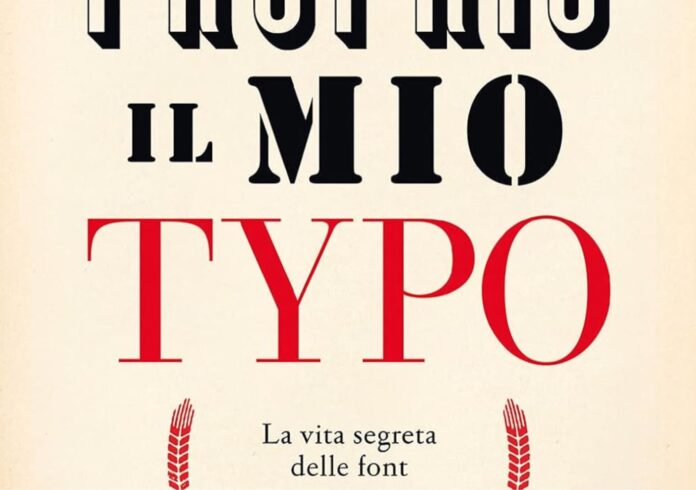
Cosa vuol dire fare un libro? Come si costruisce? Che cosa serve? Tra self publishing e stampanti laser o a getto d’inchiostro di alta qualità le possibilità di far uscire dal cassetto il nostro romanzo o il nostro poema aumenta. Ma il vero problema è un altro.
Far da sé non sempre è garanzia di qualità perché il libro, oltre a essere scritto bene e rispettando alcune convenzioni chiave, è anche un oggetto di artigianato che richiede cura e sapienza nel modo con il quale viene montato. Ecco dunque che serve sapere cose che non sono quelle semplicemente della scrittura. Almeno, non solo.
Font Ergo Sum, gratis il libro che racconta i font come non li avete mai pensati
Per molti i caratteri tipografici, font in inglese, sono una serie di voci nel menu omonimo all’interno delle app di Word, Photoshop, Illustrator e tanti altri ancora, che accompagnano i nostri documenti dando loro una “impronta” che cambia la leggibilità, ma anche l’emozione di un testo, e di conseguenza la sua forza nel lettore.
Ma i caratteri, come molte altre opere dell’ingegno umano sono il frutto di mille storie, che affondano le radici degli ultimi cinquecento anni e che sono stati capaci di rivoluzionare il mondo della comunicazione, così come lo fanno ancora oggi.
Sei proprio il mio typo. La vita segreta delle font
Piccola rivoluzione quando è uscito negli Usa, quesot saggio colto di Simon Garfield è un punto di riferimento per capire la storia di un aspetto molto particolare della tipografia. Pressoché sconosciute fino a vent’anni fa, grazie all’avvento della tecnologia informatica oggi le font sono a tutti gli effetti protagoniste del nostro quotidiano. Ma quali sono state le tappe che le hanno portate a uscire dalla ristretta cerchia di addetti ai lavori e di qualche sparuto appassionato?
La risposta è in questo saggio di Simon Garfield, che rappresenta un autentico compendio della secolare storia della tipografia, da Gutenberg ai giorni nostri, che conta oltre centomila tra font e caratteri tipografici, ognuno con le sue peculiarità e le sue alterne fortune. Condito di aneddoti sul design delle parole intorno a noi, “Sei proprio il mio typo” si impone come testo di riferimento per quanti desiderano conoscere l’affascinante mondo delle font che, come sottolinea l’autore, non sono il semplice disegno di lettere dell’alfabeto, ma costituiscono un vero e proprio veicolo di emozioni. E, come vedremo, è proprio in virtù di questa loro innata capacità comunicativa che, in molti casi, sono finite per diventare icone universalmente riconoscibili, scolpite per sempre, nel bene e nel male, nell’immaginario collettivo di ogni epoca e latitudine.
Che Carattere!: Manuale illustrato sui fondamenti dei caratteri tipografici
Un libro divertente e particolare, scritto da Davide Vasta. Questo insolito manuale si concentra su argomenti come il carattere, la misura, le classificazioni, le variazioni del design, disposizione, allineamento, editoria e combinazioni di carattere, e mira a definire tutte quelle regole che aiutano ad utilizzare meglio il lettering, al di là delle proprie preferenze di natura meramente estetica. Uno strumento sicuramente utile per trasformare l’amore per i caratteri in una operazione di scelta e ponderazione misurata e professionale, sotto ogni punto di vista.
Fare grafica editoriale. Progettare il libro: storia, teorie, tecniche e processi
Questo lavoro di Franco Achilli è quel che ci vuole per sapere come si fa a fare un libro. Serve davvero poco altro. Dedicato non solo ai visual designer, ma anche a tutti coloro che svolgono un ruolo nel processo di ideazione e realizzazione del libro, questo manuale costituisce uno strumento per accostarsi alla progettazione, attingere informazioni, utilizzare suggerimenti tecnici e apprendere quegli elementi storici e culturali che costituiscono il retroterra fondamentale del designer editoriale. Il volume affronta l’ambito della progettazione del libro attraverso tre aree distinte. La prima parte propone l’inquadramento dei contesti storici e culturali che hanno consentito lo sviluppo delle tecniche di riproduzione a stampa, dalle prime forme di scrittura al disegno dei caratteri, fino alle diverse tecniche analogiche e digitali, fornendo inoltre il profilo di alcuni giganti della grafica editoriale e della progettazione tipografica. Nella seconda parte sono presi in considerazione i temi e gli argomenti strettamente tecnici, imprescindibili per chiunque si cimenti con la progettazione del libro e degli stampati di qualità: dai formati ai diversi tipi di carta, dal trattamento delle immagini alla riproduzione del colore, dalla confezione alla scelta delle finiture. La terza parte costituisce un’introduzione alla disciplina di progetto e al significato specifico della grafica editoriale in tutti i suoi aspetti, dall’editing all’impaginazione, dalla gabbia alla copertina. Vengono analizzati anche i temi legati alla marca e al marketing editoriale, al packaging come espressione valoriale del libro per trattare poi l’azione produttiva, con focus sui passaggi che, a partire dal testo iniziale, portano alla consegna del libro al punto vendita o al committente. Il manuale si completa con un glossario generale dei termini in uso nella progettazione e nella produzione, e con una bibliografia ragionata. Prefazione di Armando Milani.
Manuale del rilegatore
Fare un libro può voler dire anche saperlo rilegare. All’interno del libro di Gabriella Polverari Dell’Orto c’è l’immancabile breve storia del libro e della rilegatura, ma anche u materiali, le macchine, gli attrezzi, le tecniche particolari per le operazioni ricorrenti, le operazioni preliminari alla legatura. Le guardie, la cucitura, la lavorazione del corpo, la copertura del libro incartonato, la copertina a cartella. Seguono l’asciugatura, i controlli e le rifiniture, la rasatura e le decorazioni dei tagli. La rilegatura senza cucitura e l’aggiustatura di precedenti rilegature sono il complemento finale a cui si accoda un ricco glossario.
Il dettaglio in tipografia. Un’analisi breve e concisa delle questioni che riguardano la leggibilità dei testi
Quand’è che un libro è ben leggibile? Una buona impaginazione può certamente catturare l’attenzione, ma quando i dettagli non sono curati, la lettura richiede uno sforzo eccessivo e il piacere finisce subito. In questo agile volumetto Jost Hochuli, uno fra i più noti e apprezzati grafici svizzeri, spiega come assicurare ai lettori la miglior esperienza possibile.
Per farlo ci introduce al mondo del dettaglio tipografico o della microtipografia e analizza uno per uno i suoi elementi costitutivi: lettera, spazio tra le lettere, parola, spazio tra le parole, riga, interlinea e colonna di testo. Sono tutti aspetti spesso trascurati dai progettisti grafici perché non rientrano nella sfera creativa, ma dai quali dipende la leggibilità del testo. Attraverso esempi e casistiche, Hochuli segnala problemi e indica soluzioni, stimola acume e senso critico per poi invitare ogni grafico ad assumersi la responsabilità di decidere con coerenza, buon senso e sensibilità tutte le volte che la professione glielo richieda.